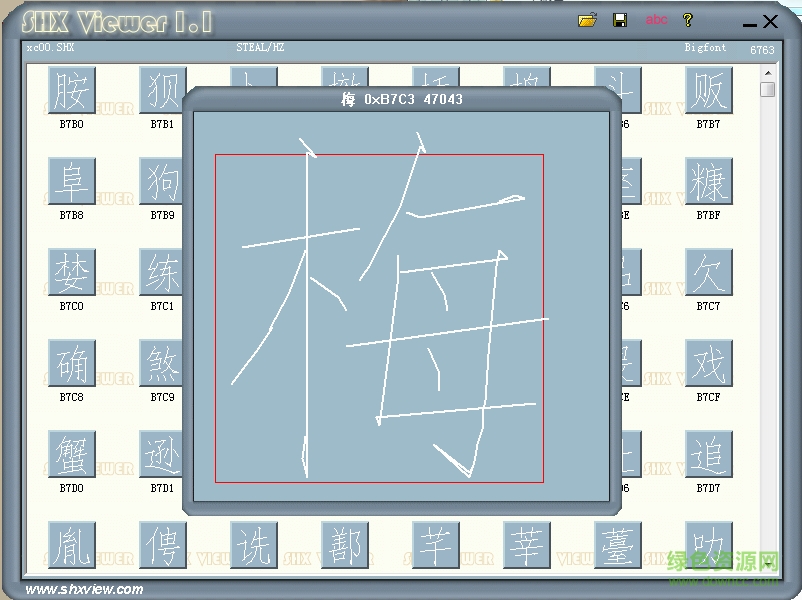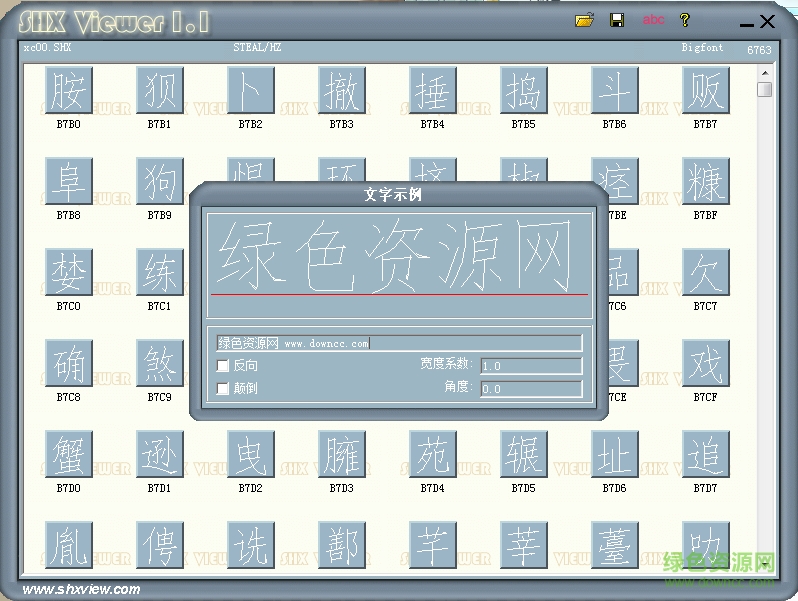
xc00.shx是一款擁有6763個(gè)漢字的cad字體,字體居中干凈清晰,用等寬線條勾勒,有著極佳的視覺(jué)美感和觀賞體驗(yàn),很多朋友在這款字體,今天綠色資源網(wǎng)免費(fèi)為大家分享哦!
xc00.shx在建筑中使用較廣,字體纖細(xì)娟秀,有著舒適的視覺(jué)呈現(xiàn),線條簡(jiǎn)明得體,讓平面設(shè)計(jì)、建筑標(biāo)記、廣告策劃的朋友使用更方便。